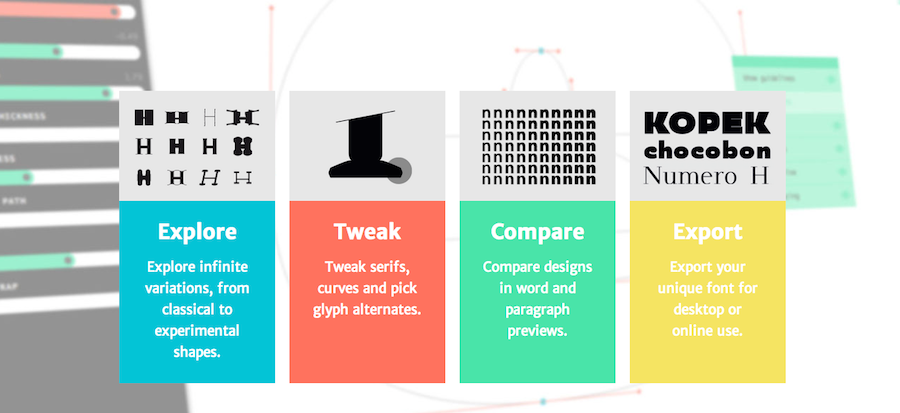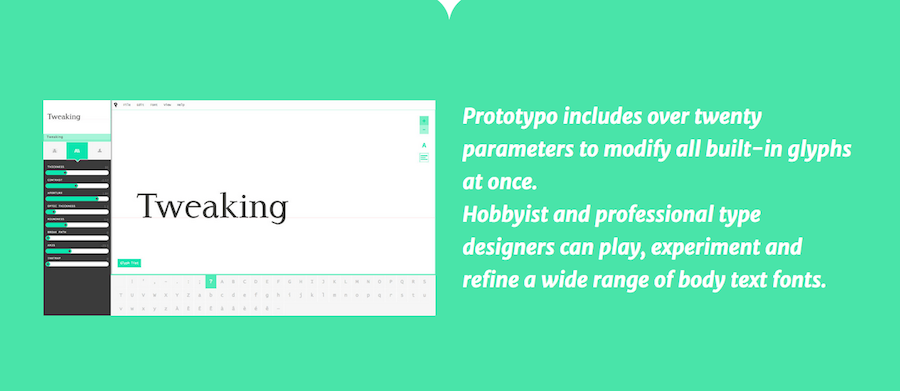
Una lista interminable de tipografías predeterminada en la pestaña que abres y no te convence ni una sola de ellas para lo que querías hacer en este momento. La que no es muy fina es muy gruesa, y la que no está hecha con dibujitos de soles y lunas da la sensación de salir de una casa encantada. Los fabricantes de estos alfabetos de plantilla no te comprenden. Como solución te queda buscar en la red alguna otra con licencia y pagar por obtenerla. También la de llamar a un diseñador para que te cobre por unas letras que alcancen tus expectativas. Y ahora hay una tercera vía: Prototypo «es la aplicación que te ayuda a crear tu estilo de letra perfecto sin ningún conocimiento informático», explican sus creadores.
Yannick Mathey y Louis Rémi-Babe son dos jóvenes franceses que creían que había algo más que ofrecer al público que centenares de tipografías a elegir, ya fueran gratis o de pago. Su mentalidad de código abierto les decía que lo realmente útil era permitir a los buscadores de letras, aunque no tuviesen ni idea de informática, hacer exactamente lo que ellos quisieran. Ellos dos se encargarían de ponérselo bien fácil.
Su herramienta, apta para que la utilice cualquier tipo de usuario -sea o no sea docto en la materia- es un programa que permite crear  y descargar tus fuentes tan solo con seguir unos pasos muy básicos. «En total son 20 parámetros que sirven para modificar todos los glifos incorporados a la vez», explica Rémi-Babe. «Cualquiera podrá experimentar, jugar y perfeccionar dentro de una amplia gama para formar textos con cuerpos únicos».
En muy poco tiempo comprobaron cómo la gente agradecía eso de que les dieran la caña y no los peces. Ahora cuentan con centenares de nuevas visiones estéticas del abecedario hechas por sus fieles, las cuales también puede reusar o remodificar cualquiera. «A los usuarios normalmente les gusta agarrar una tipografía que ya existe y cambiarle pequeños aspectos como sus curvas, el serif, los estilos…», aporta el creador. «Con nuestra idea adquiere el derecho de modificar todo eso libremente, a su manera».
Aunque su aplicación ya está abierta y funciona en navegadores como Internet Explorer, Google Chrome, Mozilla Firefox y Safari, ellos pretenden culminar con éxito una campaña de crowdfunding para desarrollar mucho más las capacidades del programa.
«El software soporta actualmente de la A a la Z glifos y estilos predefinidos», explican sus aspiraciones, «pero queremos ofrecer nuevas herramientas en Prototypo que contemplen aspectos como el espaciado, el kerning conjunto o los pictogramas alternativos». El alfabeto ya estaba inventado y la repetitiva manera de reproducirlo en Arial o en Times New Roman también. Ellos se comprometen a lograr que, a partir de ahora, cada uno escriba en el ordenador con su propia letra.